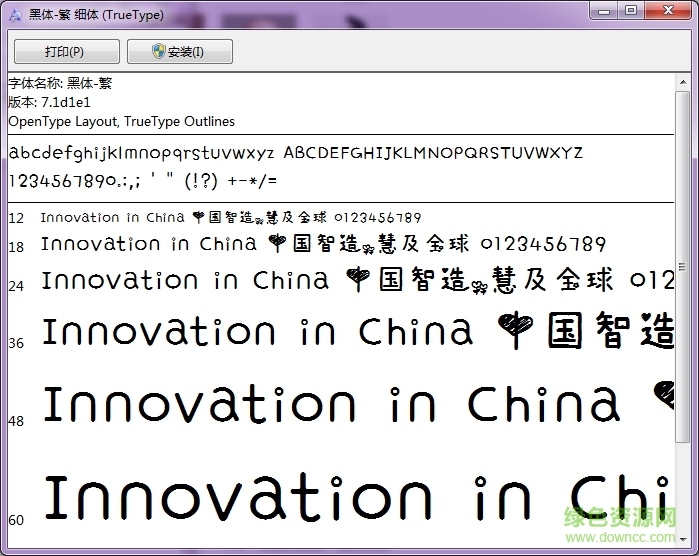
小兔黑體簡寫是一款非?;顫娪腥さ?a href="http://573ee.cn/k/katongziti/" target="_blank">卡通字體,可愛的花樣點綴和心形修飾,讓文字更加生動,無論中文還是英文都有著獨特的視覺呈現(xiàn),喜歡的朋友就來綠色資源網(wǎng)免費下載吧!
小兔黑體簡寫體兼具了藝術(shù)字體和手寫字體的特點,給人童稚的樂趣和舒適的閱讀體驗,可以廣泛運用于藝術(shù)設(shè)計、海報設(shè)計等諸多領(lǐng)取,還可以安裝在手機上哦!